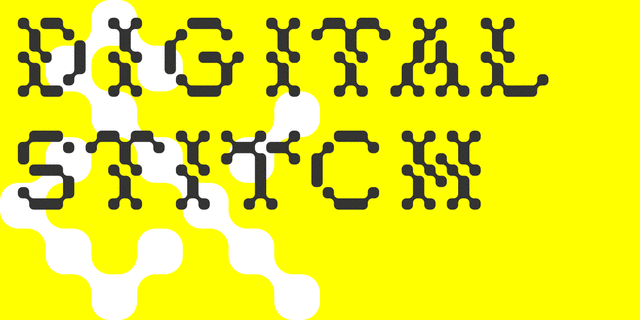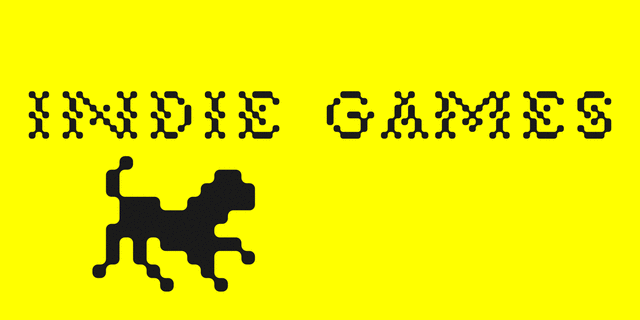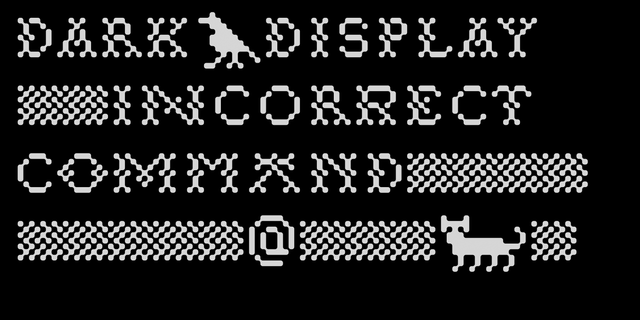
Digital Stitch – это вышивка цифровой эры. Этот шрифт представляет собой смесь пиксельной графики, традиционной вышивки крестиком и печатных плат. Поддерживает много языков и содержит орнаменты и картинки. Шрифт разработан Лукьяном Турецким в 2013 году.
оригинальный, характерный, странный, загадочный, компьютерный, игривый, забавный, необычный, экспериментальный, прикольный, ужасный, страшный, мистический, таинственный, дробный, молодежный, инопланетный, кислотный, экзотичный, психоделический